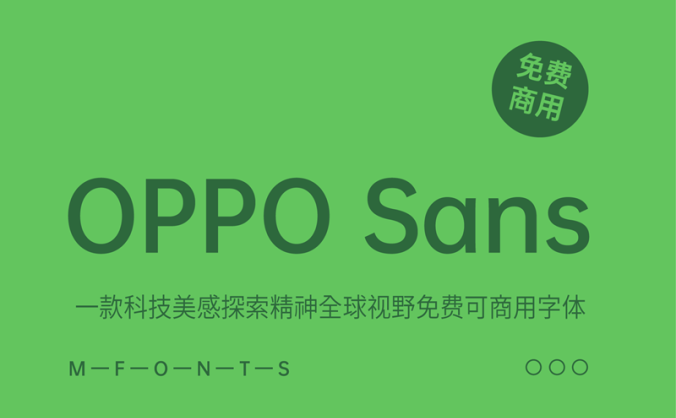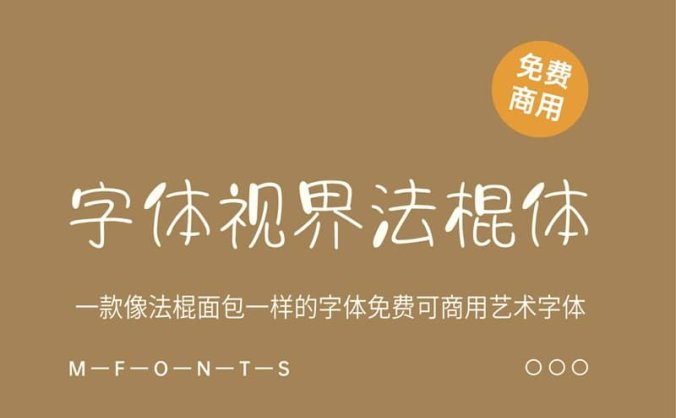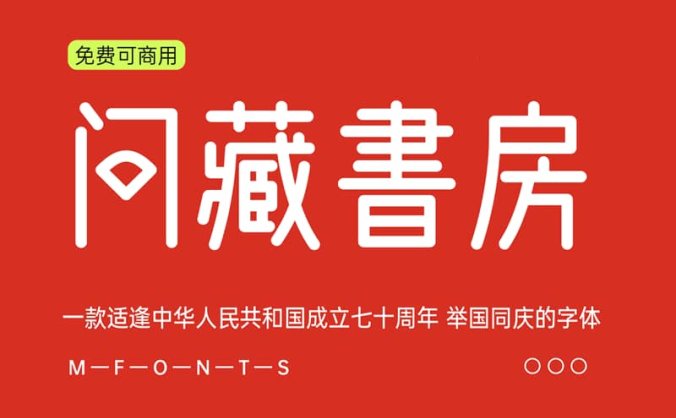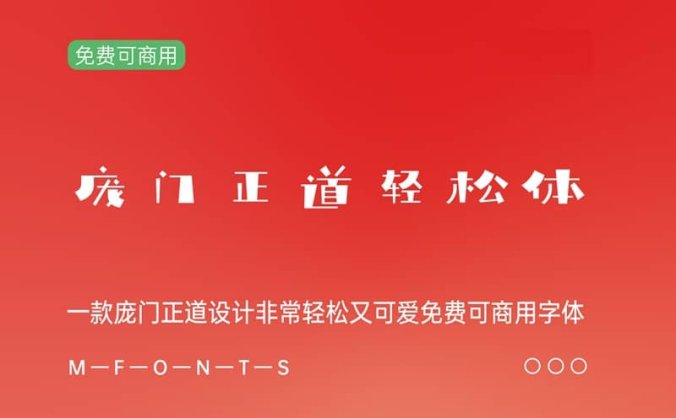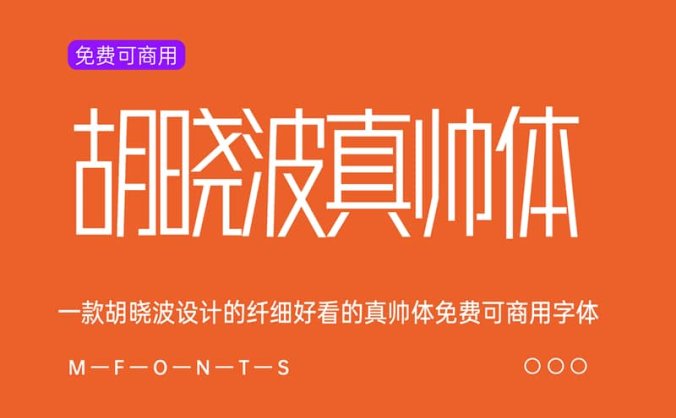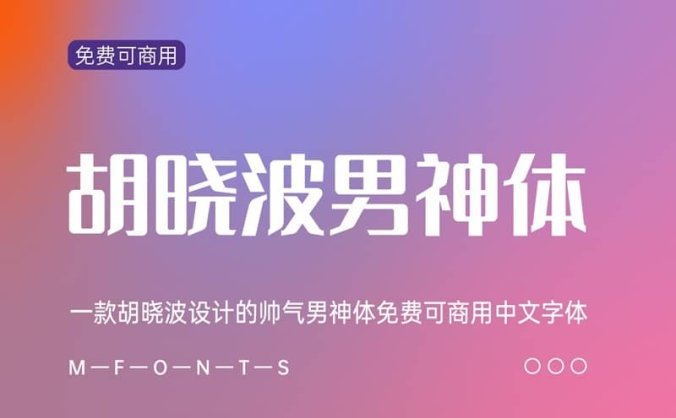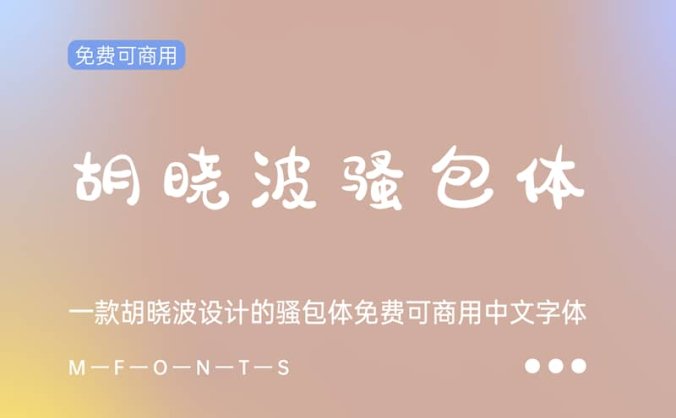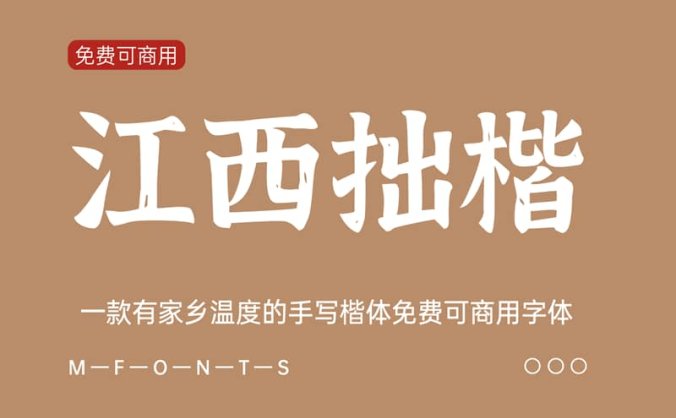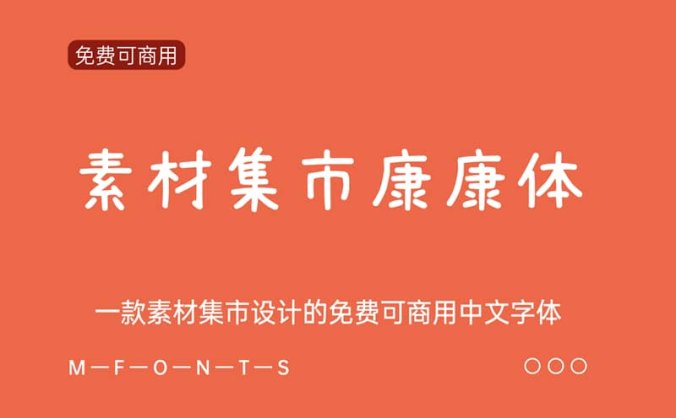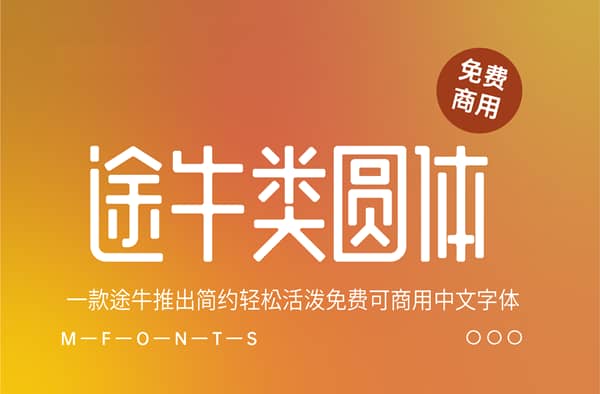
《OPPO Sans 4.0》一款科技美感探索精神全球视野免费可商用字体
字体介绍: 2019年11月20日,在OPPO第二个十年的开端,OPPO希望从产品到品牌都能为用户带来全新的体验。所以,全新的OPPO Logo应运而生,它化繁为简,更加包容。除此之后,还伴随着一套属于OPPO的品牌字体诞生,那就是「OPPO Sans」,它针对移动端做了很多像素级的优化,长时间阅读也不累。 OPPO Sans中文部分由汉仪字库字体设计总监朱志伟指导,黄珍元设计完成,西文部分则由美…- 1k
《字体视界法棍体》一款像法棍面包一样的字体免费可商业艺术字体
《问藏书房》一款适逢中华人民共和国成立七十周年 举国同庆的字体
字体介绍: 问藏书房是造字工房创始人丁一将二十余年收藏和学习的数千本设计、绘画、摄影、字体等艺术图书全部捐助于问藏书房而创建。意向通过问藏书房免费借阅给对设计与艺术、美学类相关知识有兴趣的同学。在各界朋友的帮助和造字工房创新资金全力支持下,投入数百万元,将艺术与美学类书籍的藏书量增至万余册,一并无偿开放借阅给热爱书籍、对审美有更高需求的朋友们,以实际行动为中国的审美教育贡献一份绵薄之力! 适逢中华…- 740
《庞门正道轻松体》一款庞门正道设计非常轻松又可爱免费可商用字体
字体介绍: 2019年12月5日,在这个特别的日子里,庞门正道第三套免费商用字体庞门正道轻松体正式上线。这款字体是刘兵克字体设计班的学生在自愿的原则下,一共78位学员经过了一年的努力开发的字体。这是一次免费的公益字库的设计,大家都是没有额外的金钱报酬的,仅仅是为了社会公益,社会价值。 庞门正道轻松体字库风格非常可爱蠢萌,带着些许的俏皮的,趣味十足,字形活泼非常适合宠物,儿童等方面的设计。- 709
《胡晓波真帅体》一款胡晓波设计的真帅体免费可商用字体
《胡晓波男神体》一款胡晓波设计的男神体免费可商用字体
字体简介: 胡晓波男神体是胡晓波字体开发的一款非常有个性的中文字体,该字体线条粗细适中,字形端正大方得体,风格上比较有艺术风格,可以应用于文本装潢、信息展示、网页设计、篆刻制模、数据制作、装潢设计、计算艺术设计、视觉设计、字帖等一切合法应用场景,有喜欢的朋友可免费下载收藏。- 1k
《胡晓波骚包体》一款胡晓波设计的骚包体免费可商用字体
《江西拙楷》一款有温度的手写楷体免费可商用字体
字体简介: 这是一套手写楷体,相比电脑中标准化制作的楷体,这套字体的笔画会带有一些书写的痕迹,每个字的笔画是没有统一标准的,所以看上去显得不够规范,但是会有一种手写的自然之感。这套字体从写手稿开始到今天的最终成品,前前后后花了近半年时间,仅仅是调节点,就花了20多天,其中的滋味做过才知道。- 821
《素材集市康康体3.0》一款素材集市设计的免费可商用字体
字体简介: 3.0版本由字集团队成员 时光羊 独立完成,用了近6个月时间,在1.0版基础上增加5131个字补齐GB2312-80编码字库,目前汉字和字符共计7754个。- 615
《途牛类圆体》一款途牛推出简约轻松活泼免费可商用中文字体
字体简介: TUNIUGB – NARROW字库公测发布。提供1000个常用字限时免费下载! 我们认为契合旅游行业呈现的字体应有某些特质: 简约、轻松、活泼、流畅! 但是市面上的大小字库,鲜少能够兼顾这些特质。于是我们萌生了设计一套针对特定场景下使用的字库的念头,结果我们失败了!因为猝不及防地发现,它居然还挺百搭~ ~ 整套字库将圆体作为基本型以满足两点诉求,除了上文所述,还有一项是较强的可塑性。…- 443
《卓健橄榄简体》一款简约流畅科技感的免费可商用中文字体
字体简介: 2019即将接近尾声,在新的一年即将来临之际,卓米设计团队年终献礼——卓健橄榄简体限时免费下载,免费商用。 文字、图形、色彩是平面设计信息传达的三要素,而字体则是这三要素中的重要因素之一,在字体类型众多的市场中,卓健橄榄简体有着独树一帜的时尚风格,如今,这款字体首次提供7050个常用字限时免费下载。 最重要的是免费商用!免费商用!免费商用! 从调研——定位——草图——规范——成稿,我们…- 430
《汉字拼音体》一款帮助学生更快地学习和阅读汉语免费商用字体
字体简介: 汉字拼音体(Hanzi-Pinyin-Font Regular)是一款比较特别的字体,这款字体的文字头上自带拼音。 这是一种用来帮助学生更快地学习和阅读汉语的字体。在某些设计场景其实也挺实用的,特别是对教育类的设计比较有用。 该字体简体繁体都支持得挺好的。 汉字拼音体是遵循CC-BY-SA-4.0授权协议,可以免费用于商业用途、发布,修改,私用等。- 584
《思源宋体》一款支持4种语言7个字重的文学性衬线体免费字体
字体简介: 思源宋体(Source Han Serif)是 Adobe 与 Google 合作发布的最新泛 CJK 字体,它是对应于思源黑体的宋体字体;旨在提供一个可以涵盖 Unicode 全部字符的多语言、全方位字型,响应统一设计的需求,以服务于东亚 15 亿人口。 思源宋体属于衬线字体,支持简体中文、繁体中文、日语和朝鲜语,拥有 7 种字重,且每一种都有 65,535 个字形,设计一致性将有助…- 565
《思源黑体》一款支持4种语言7个字重的免费可商用中文字体
字体简介: 思源黑体中的“思源”一词来自于成语“饮水思源”,是 Adobe 与 Google 历时三年时间,于 2014 年 7 月发布推出的一款开源字体。 Google 一直致力于为包括中日韩用户在内的世界各种语言用户提供高品质的信息服务。为了给中日韩用户带来愉悦和高效的信息阅读体验,Google 和 Adobe 合作开发了这款免费可商用黑体——思源黑体。 思源黑体的开发以 Adobe 的设计师…- 939
《资源圆体》一款包含7种字重的圆体免费可商用中文字体
字体简介: 资源圆体是由国内设计师 Cyano Hao 以思源黑体为基础改造而成的圆体字体。资源圆体对简体字体的支持较好,基本不会发生缺字的情况。- 1.1k
《寒蝉手拙体》一款精髓为发掘手写逼真的免费可商用中文字体
字体简介: 寒蝉手拙体,主要精髓为发掘手写字体的手拙之美,字体给人一种逼真手写的视觉体验。虽应用范围有限,但有其不可替代和独特的价值。以创造的笔意和结构完成,形成风格独特的一套小众字体。 字数:本字体基于中华人民共和国GB2312-80字符集标准,采用TrueType和OpenType两种格式,共收容字形7586个。- 752
《优设好身体2.0 》一款优设网出品的第二套免费可商用中文字体
字体简介: 优设好身体是一款亲和力、现代感极强的专业美术标题字体。它以圆体字型为基础,通过瘦高的字面、偏向几何的曲线,让整宽字体富有亲和力和时尚感。 在同样的面积里,更窄的字面就意味着能容纳更多的信息,所以这款字体非常适用在需要体现亲和力与时尚感的各类品牌宣传广告和产品包装设计的标题上。- 1k
《有字库龙藏体》一款谷歌开源字体项目手写免费可商用字体
字体简介: 有字库龙藏体是谷歌开源字体项目里面其中一款字体,按照谷歌开源字体项目的协议, 如果你想向Google Fonts字体集中追加新的字体,你的字体项目应遵循SIL Open Font License 1.1开源许可,并且在其他地方没有专有、或限制性许可版本。具体的加入协议规则请点击这里查看。 字体项目应该是在Github或者类似的开源平台上进行开发维护,具有完整的相应源文件,对公众开放并积…- 688
《IPix中文像素字体》一款适合复古游戏风格的免费商用中文像素字体
《思源屏显臻宋》一款基于思源屏显宋体优化免费可商用中文字体
字体简介: 屏显臻宋原来的名称是“思源屏显臻宋”,由于“思源”二字是版权保留字,根据OFL授权的规则,思源系列衍生字体原则上不应带有思源二字。所以,思源屏显臻宋从1.06版本开始去掉思源二字,改名“屏显臻宋”。 极限社区的chncwk同学连续30天的超长假期,被宅在家里,百无聊赖之际把思源屏显宋GB2312内的汉字筛选了几遍,修复了肉眼可见的笔画破损问题。另外重订了西文字母的衬线,让其回归较传统的…- 1k